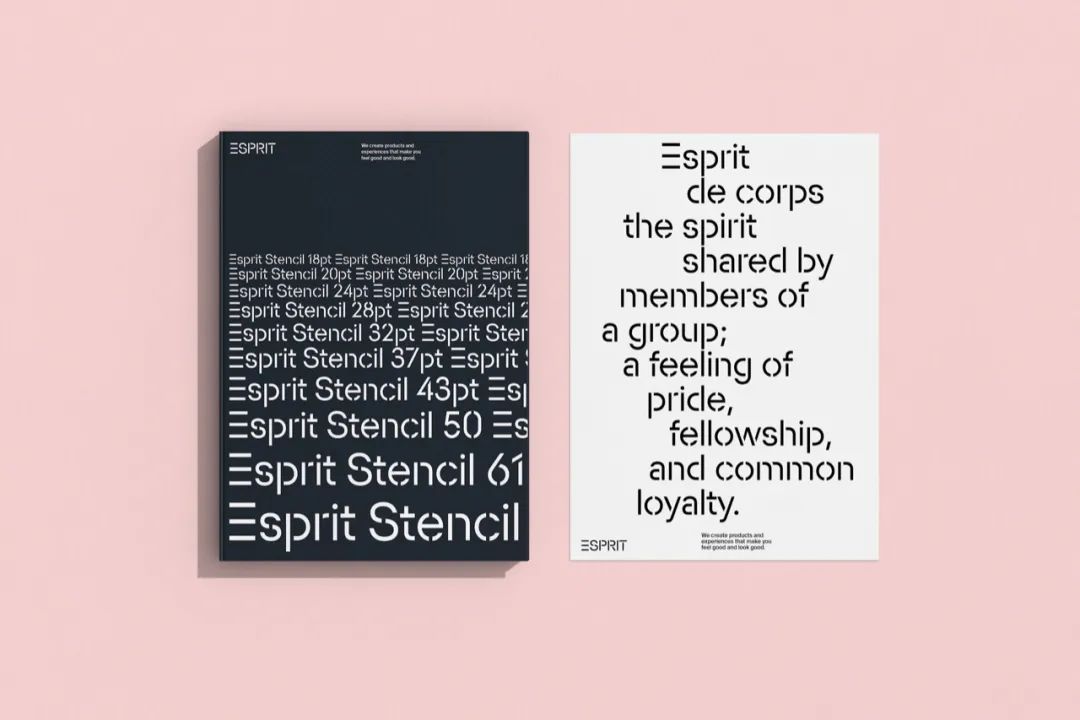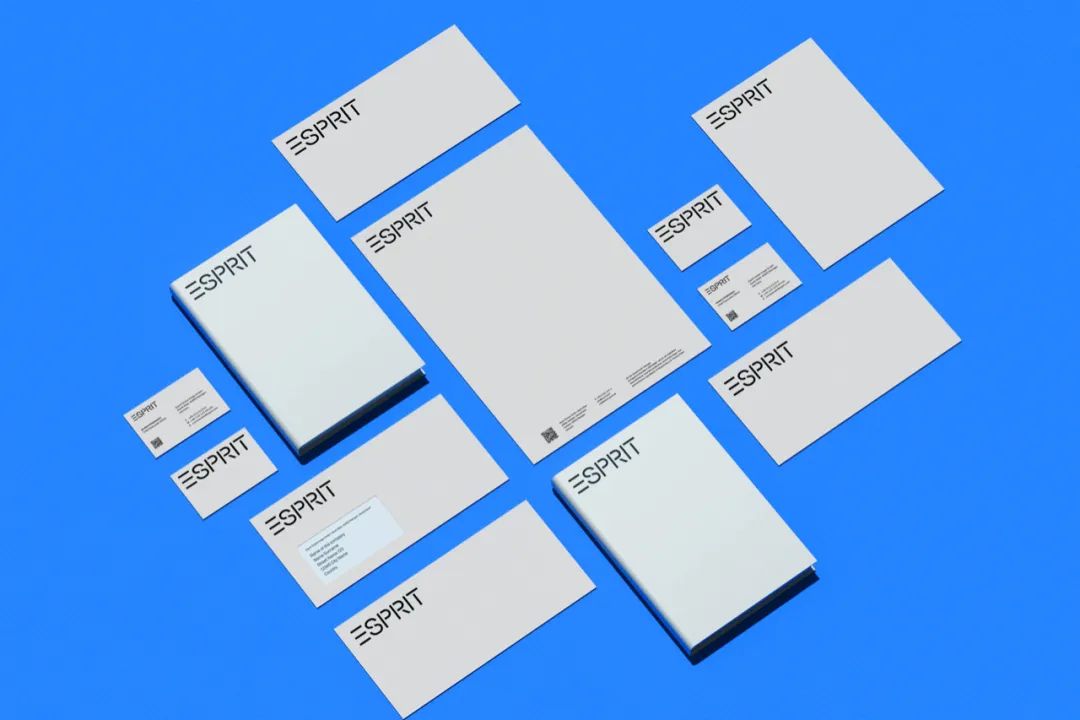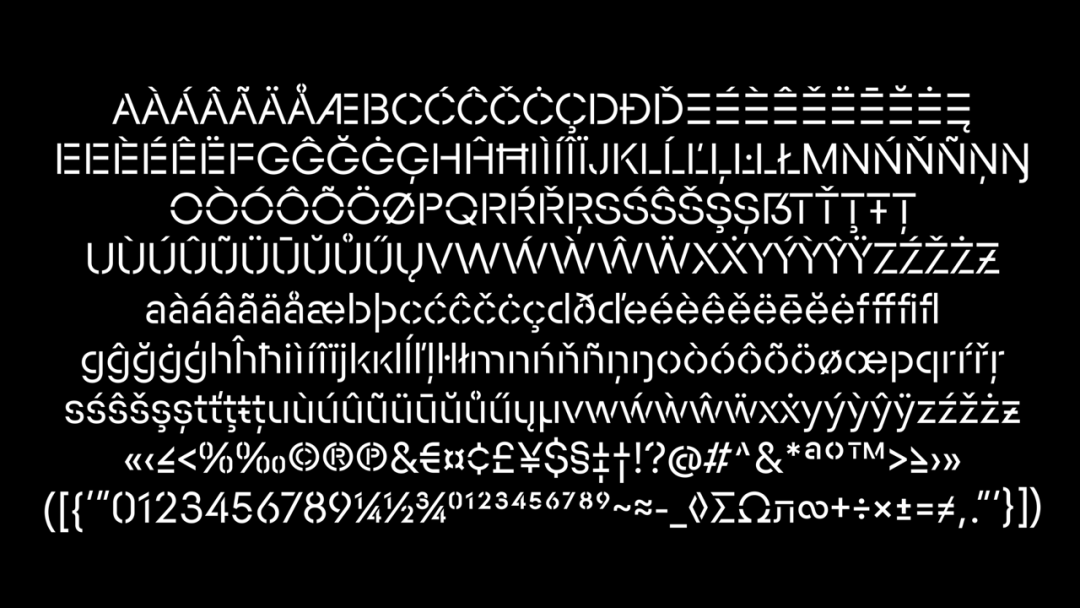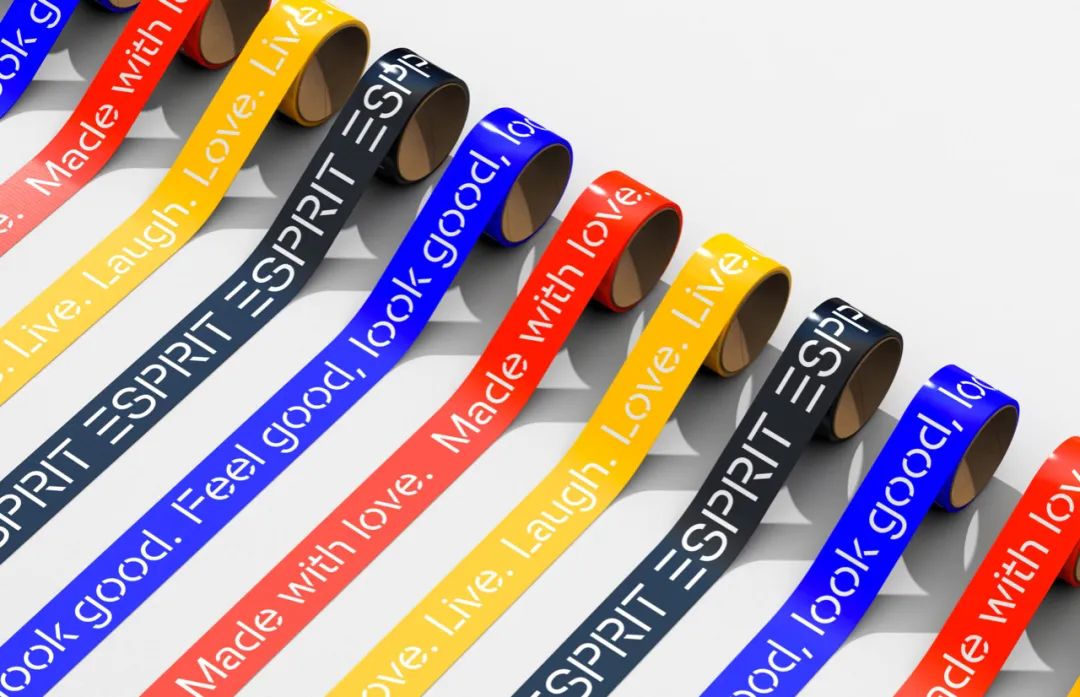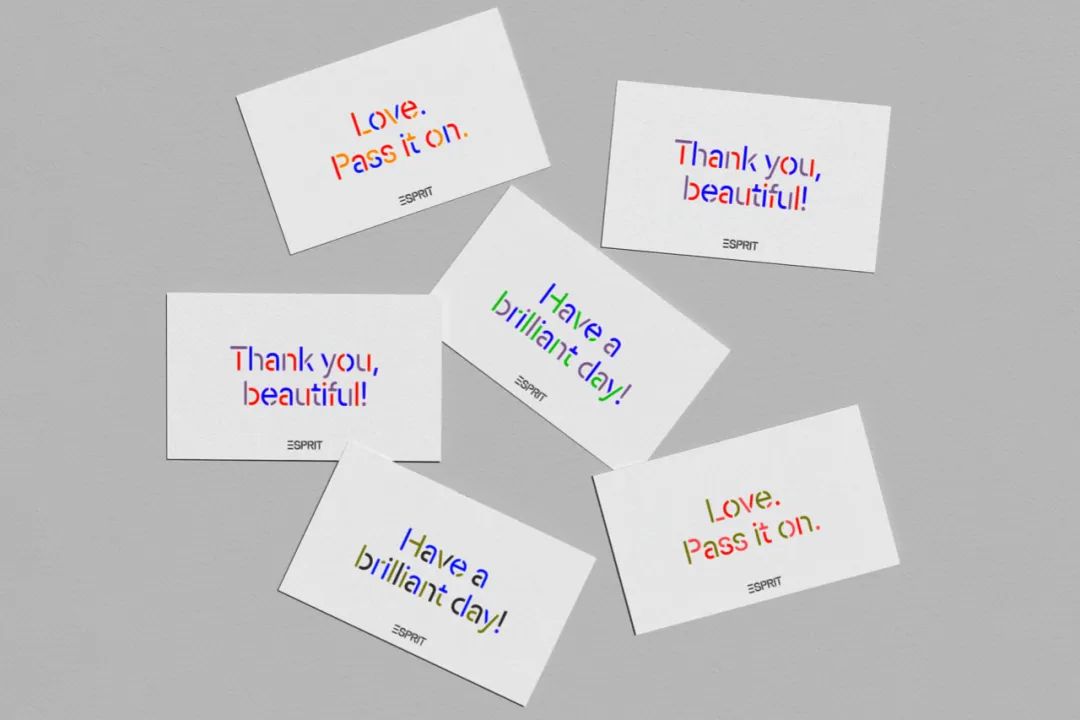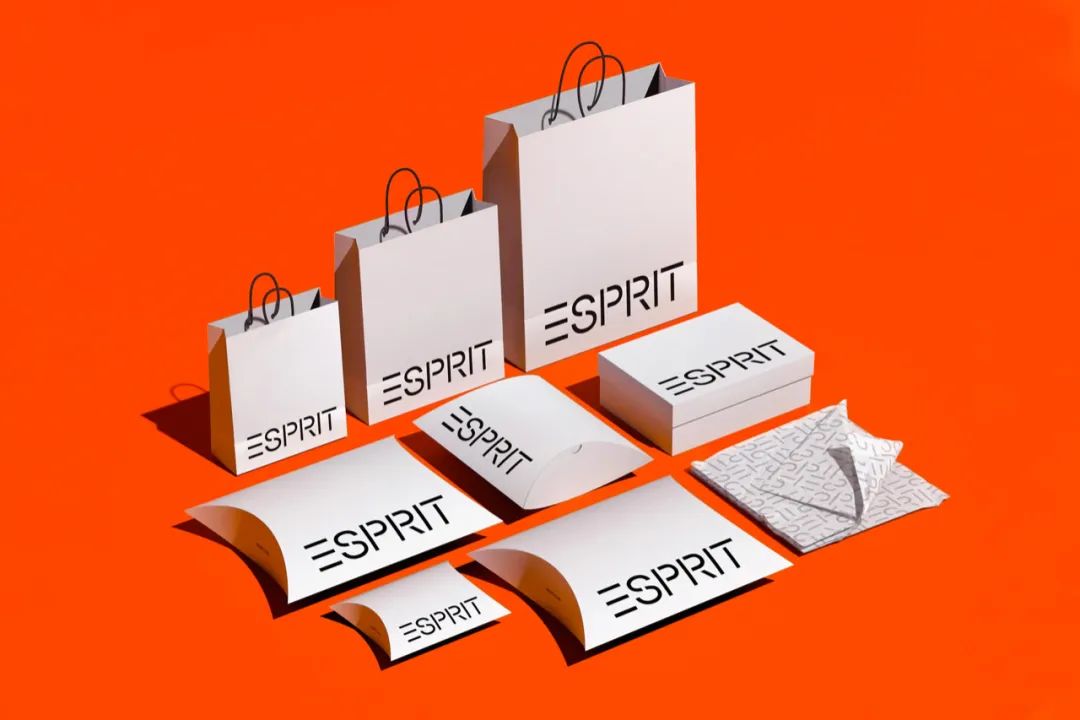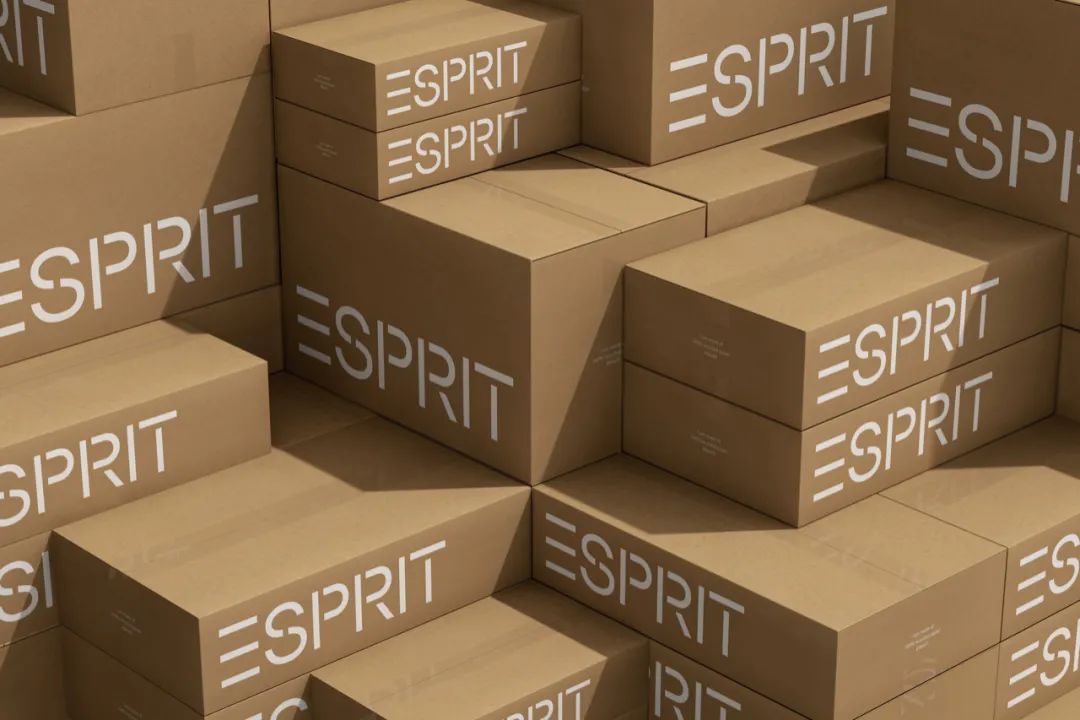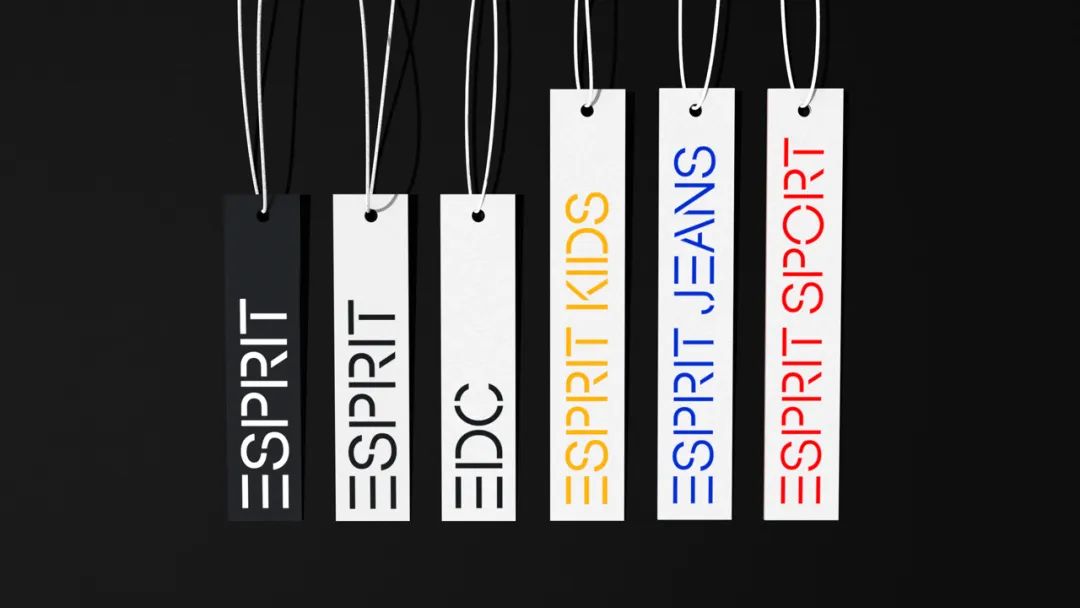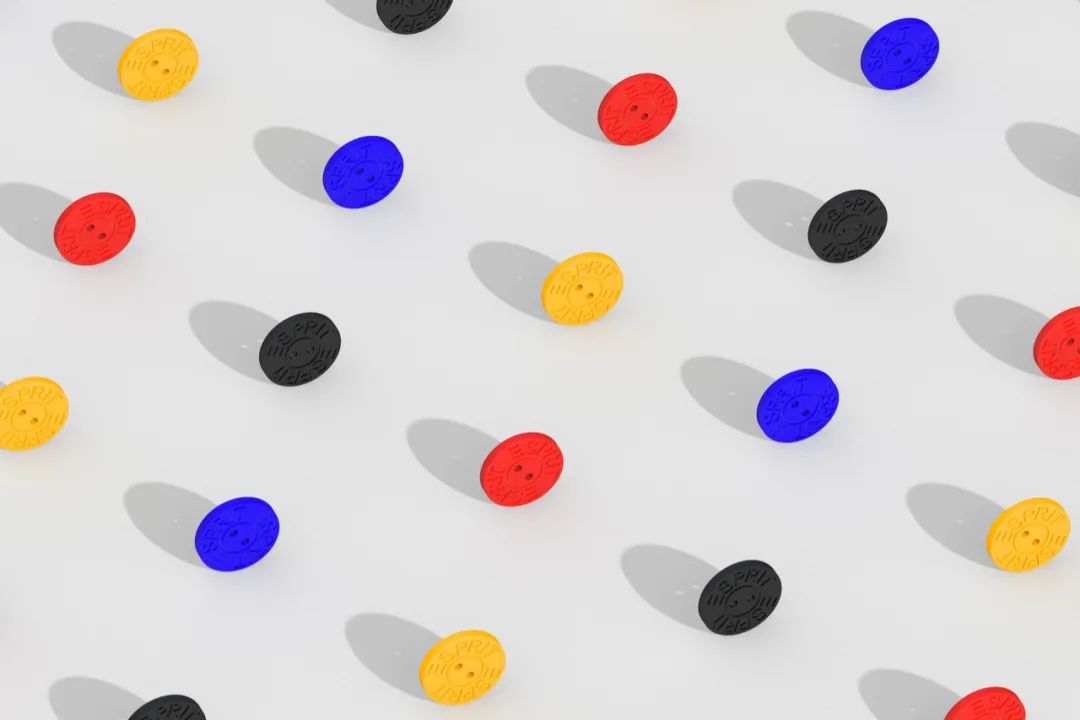
ESPRIT新形象,定制字体彰显品牌精神!
最近,ESPRIT推出了由五角设计(Pentagram)合作伙伴Natasha Jen设计的新形象。
标志经过五角设计的微调,笔画变得略细,间距也更加疏朗。
新的VI系统还重新启用了ESPRIT早期的鲜艳色彩,并设计了一套新的定制字体。
定制字体的设计灵感来自标志性的“ESPRIT”字体徽标,老徽标是一种类似喷涂模板的字体,由John Casado设计于1979年。
定制字体取名为ESPRIT Stencil,五角设计重新绘制了原来徽标字体,改进了大写字体后又着手开发了小写字体,以及数字和字形。
在版面中混合使用的ESPRIT Stencil大小写字母,以简洁时尚的面貌,传达着ESPRIT的品牌精神。同时,在动态的演示中,这套定制字体也有着不俗的表现。
建立强大的版面系统的同时,还有一套基于色相环的简单但有效的色彩系统。这套色彩系统引入72色的色相环,每种颜色由阴影(shade)、纯色(pure)和淡色(tint)三个等级,这提供了广泛色彩的可能性。
ESPRIT的设计师可以随着季节和主题而变化,在两到六对互补色中选择,并与对比色进行混合和搭配,从而得到各种不同的色彩组合,为品牌带来无限活力。
五角设计团队编辑了全面的品牌风格手册,涵盖从吊牌和标签、纽扣和拉链、包装和鞋盒、薄纸和胶带等项目。
同样的风格也延伸到ESPRIT的系列子品牌中,包括edc,Esprit Sport,Esprit Jeans和Esprit Kids等。